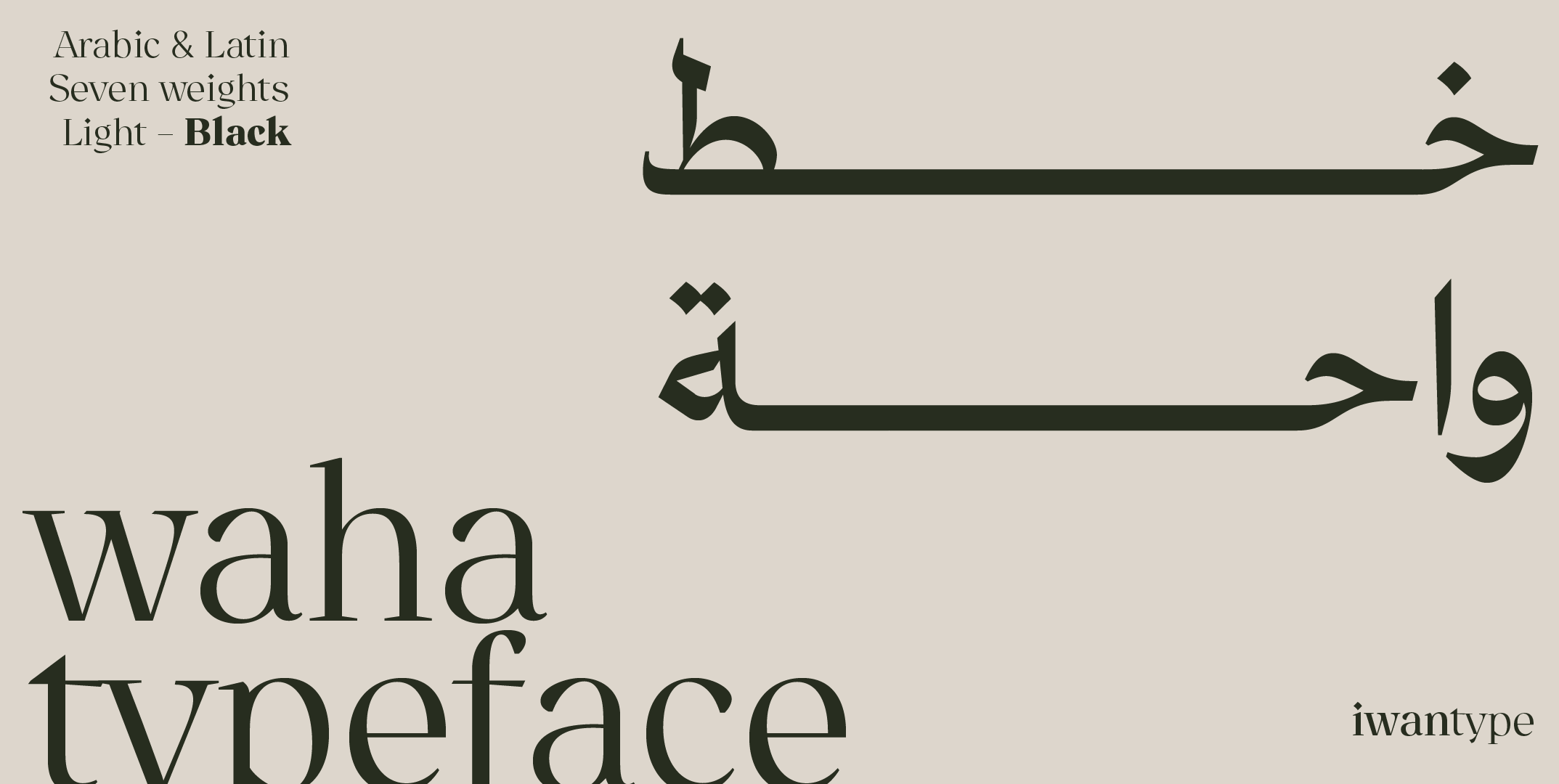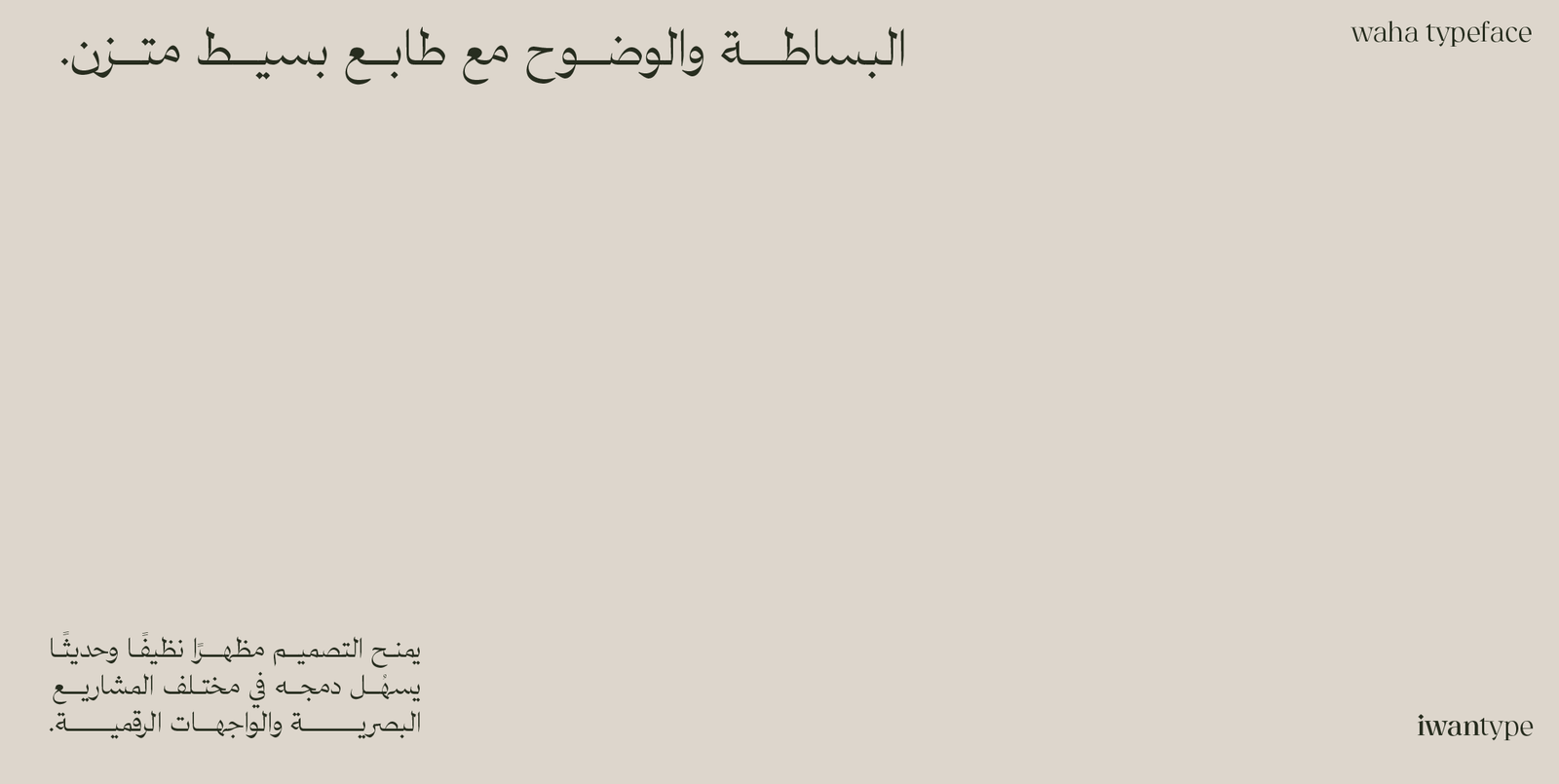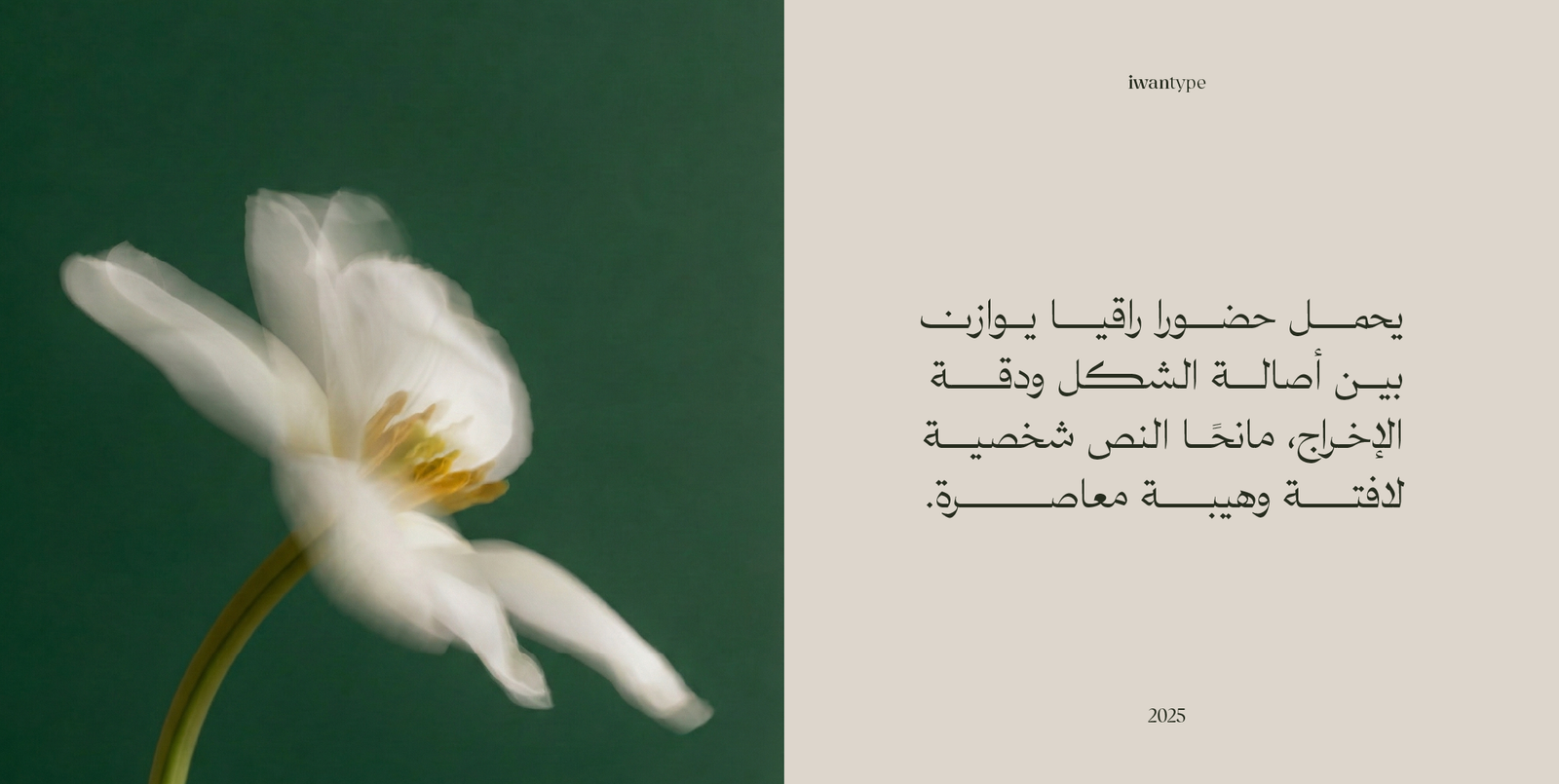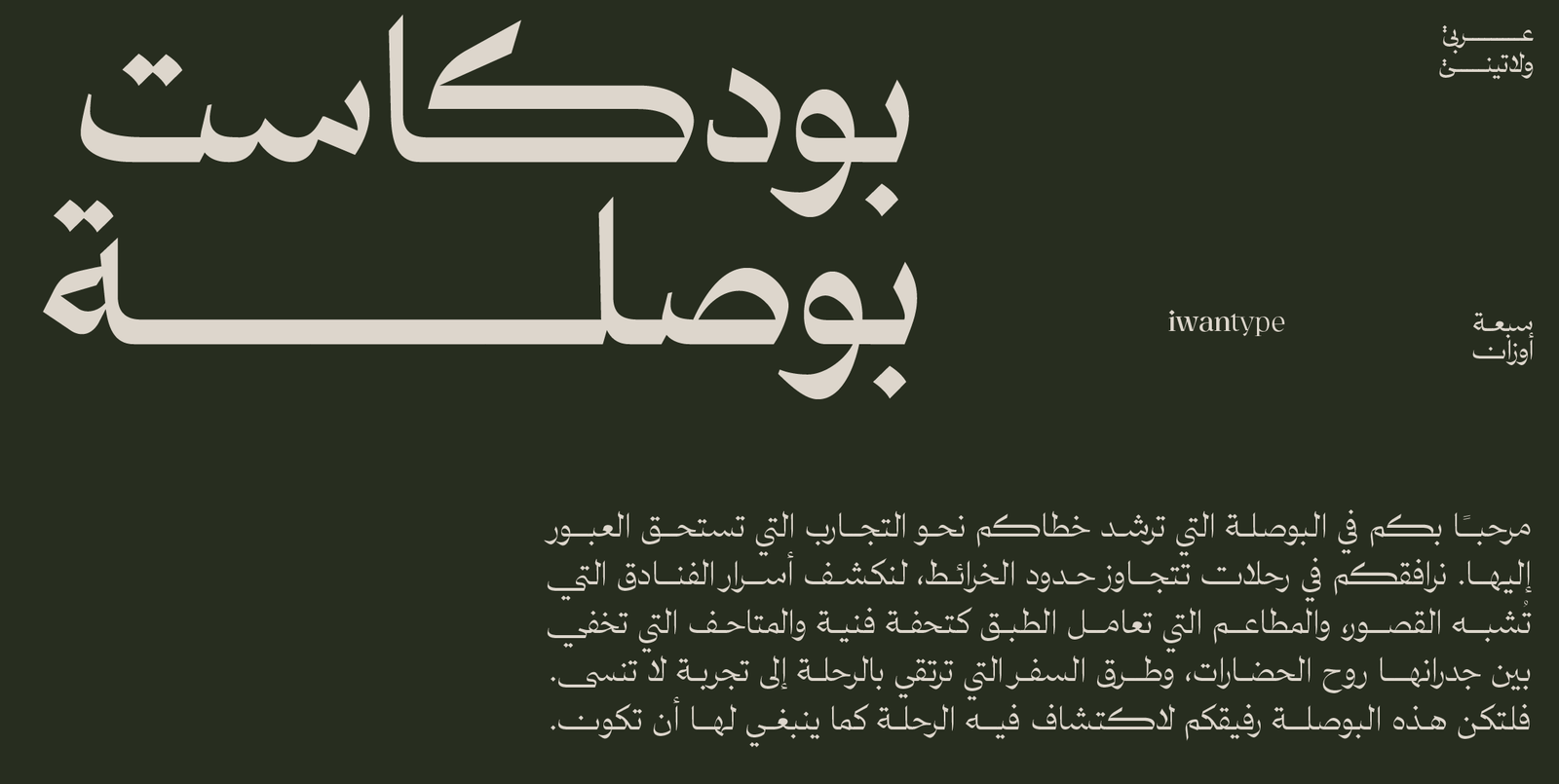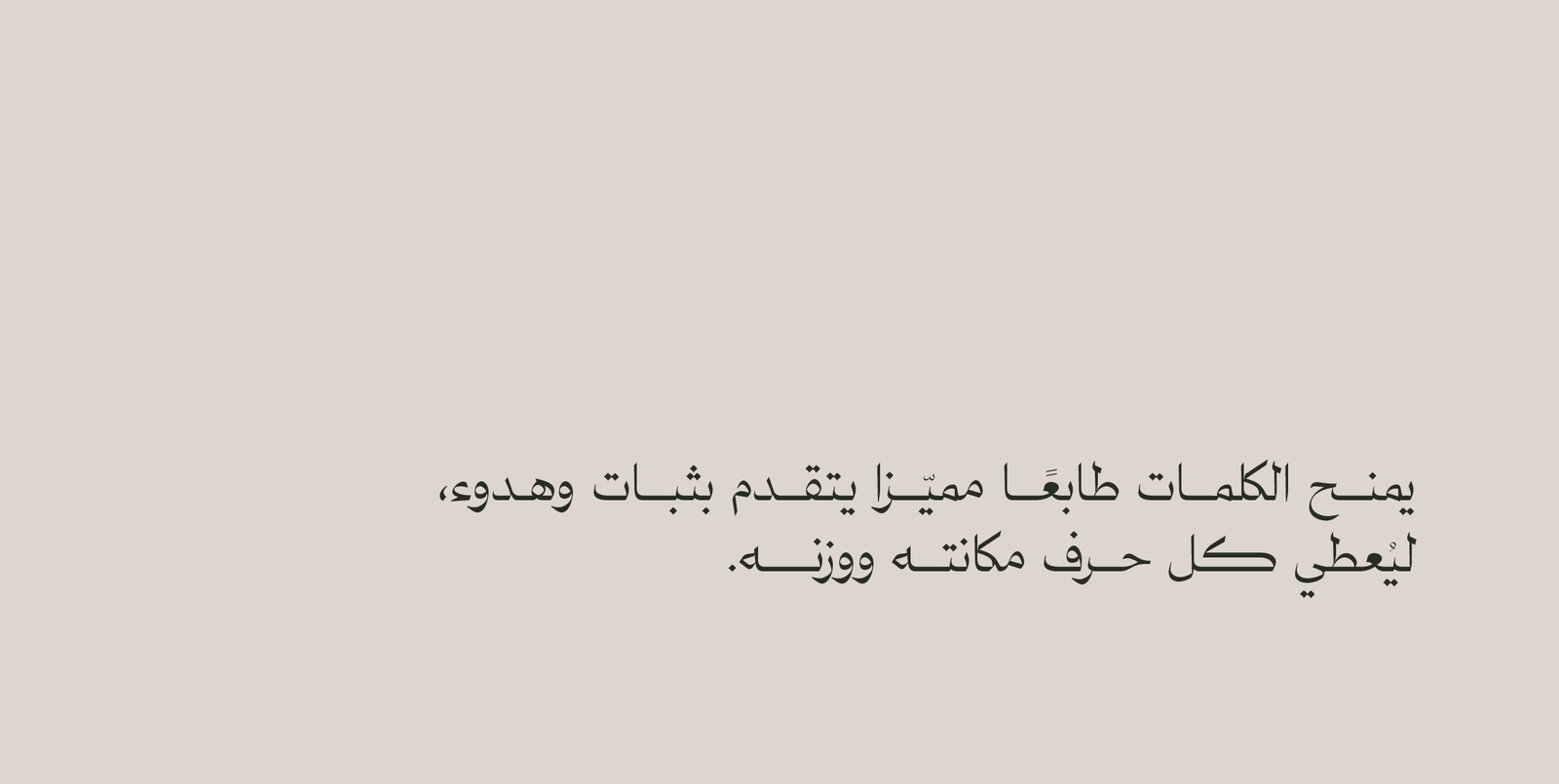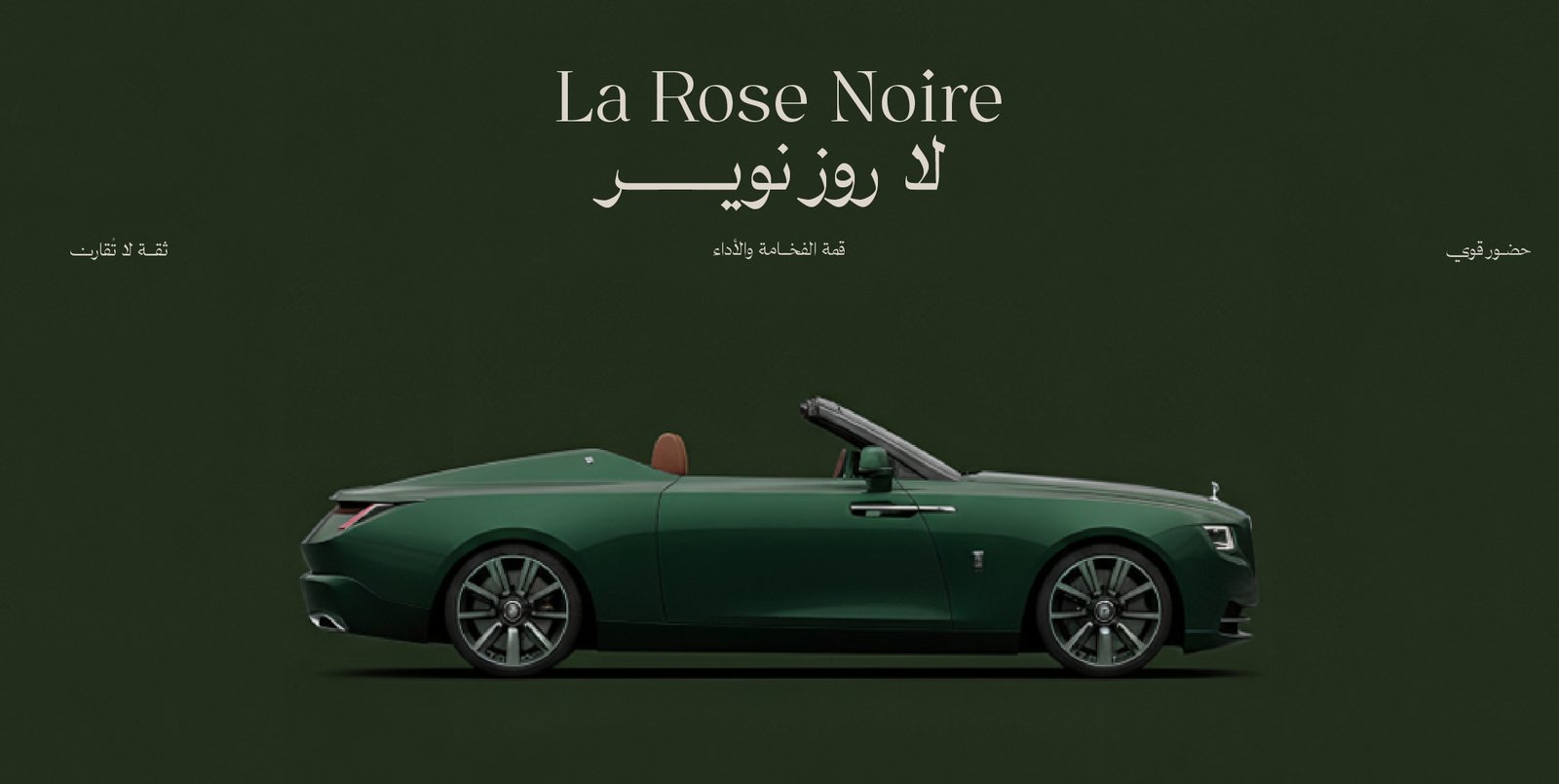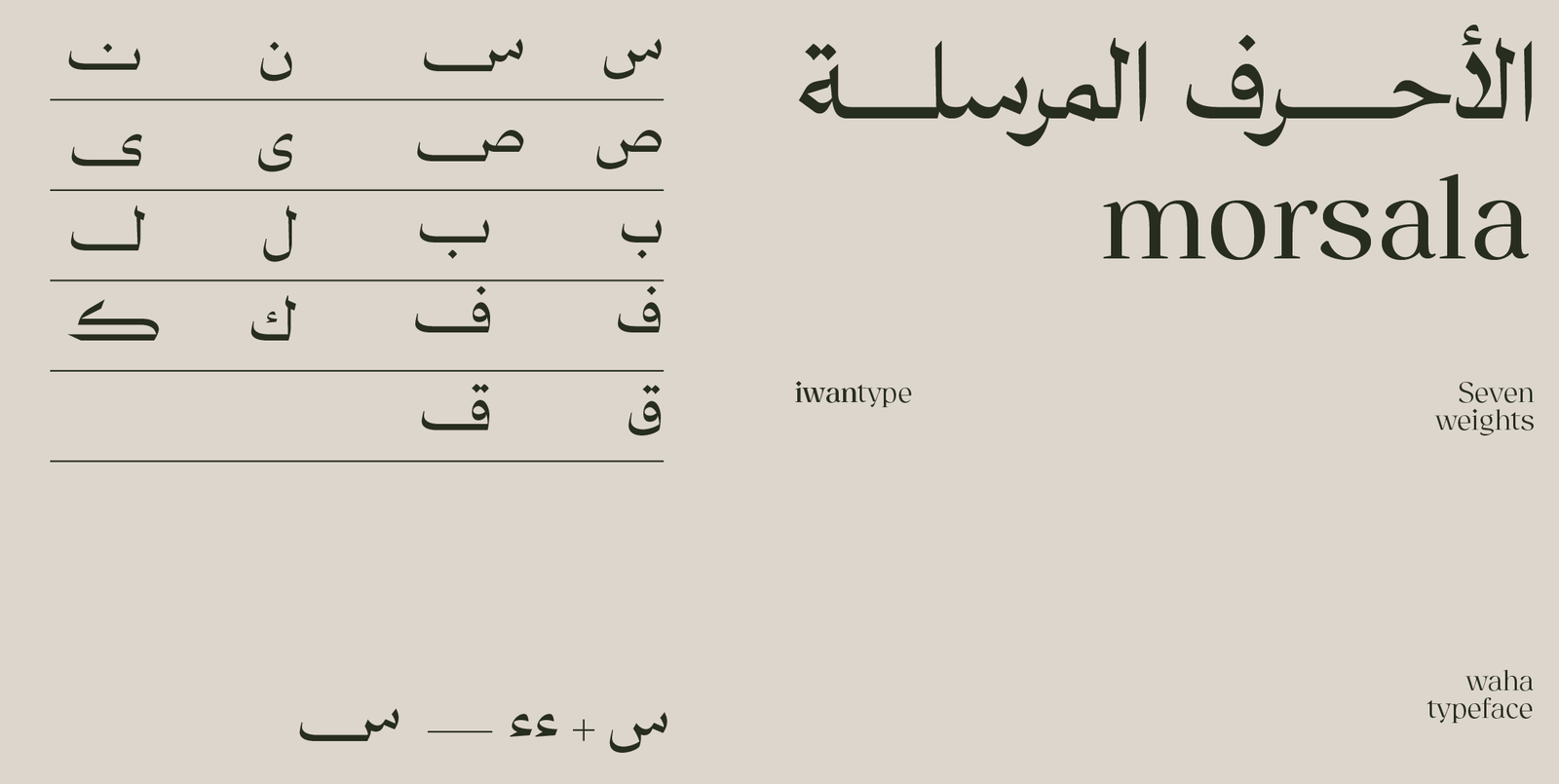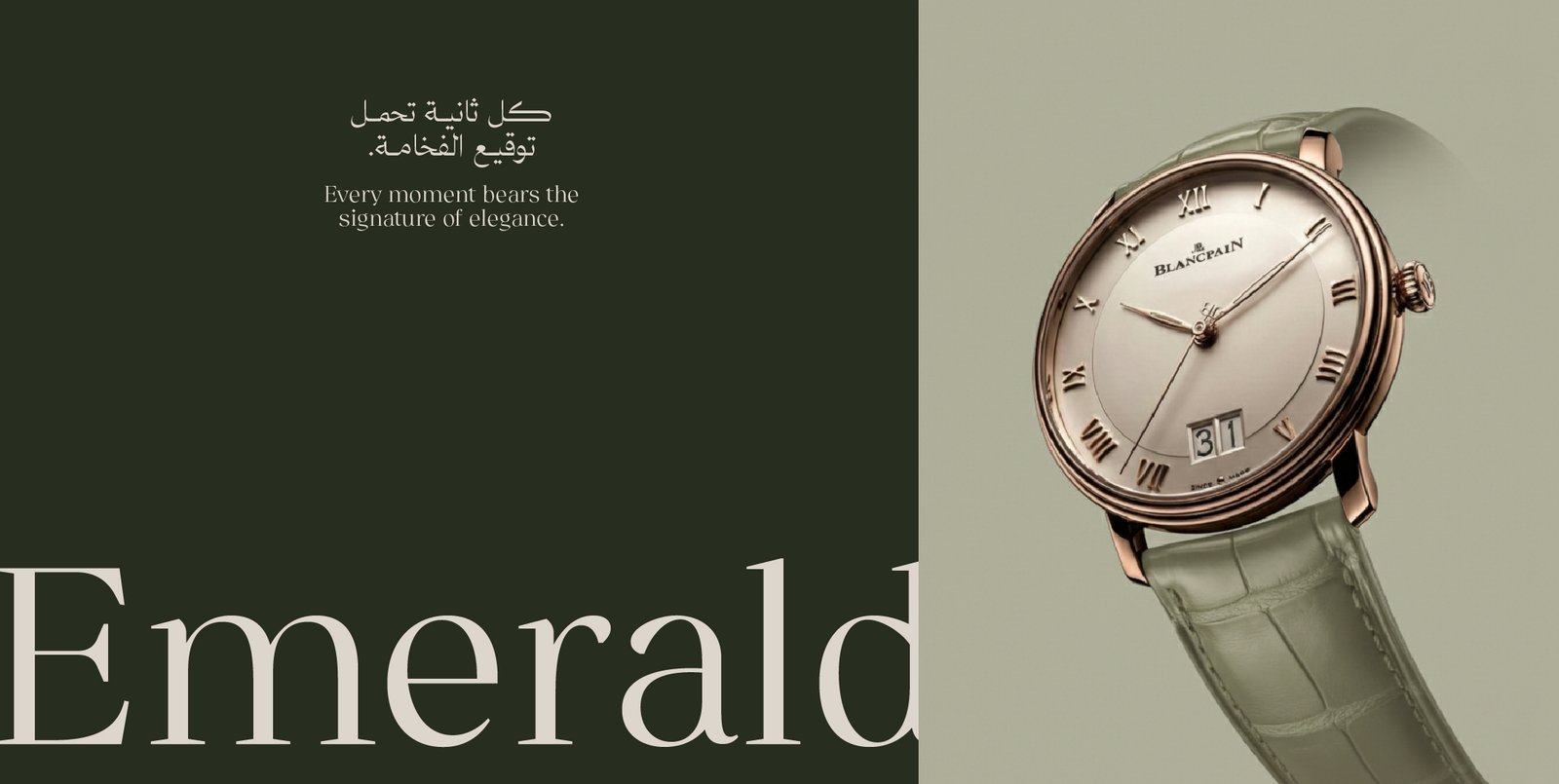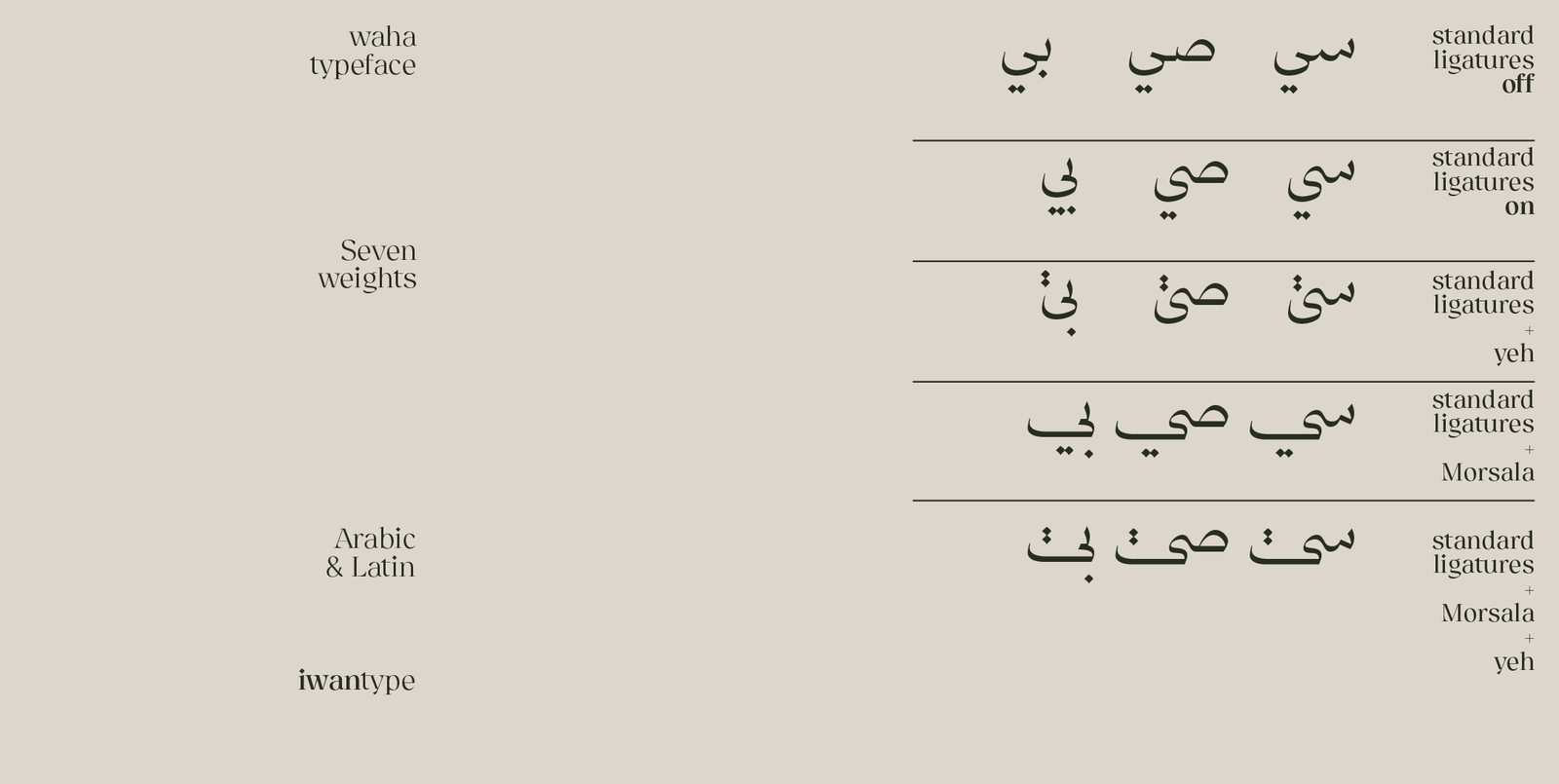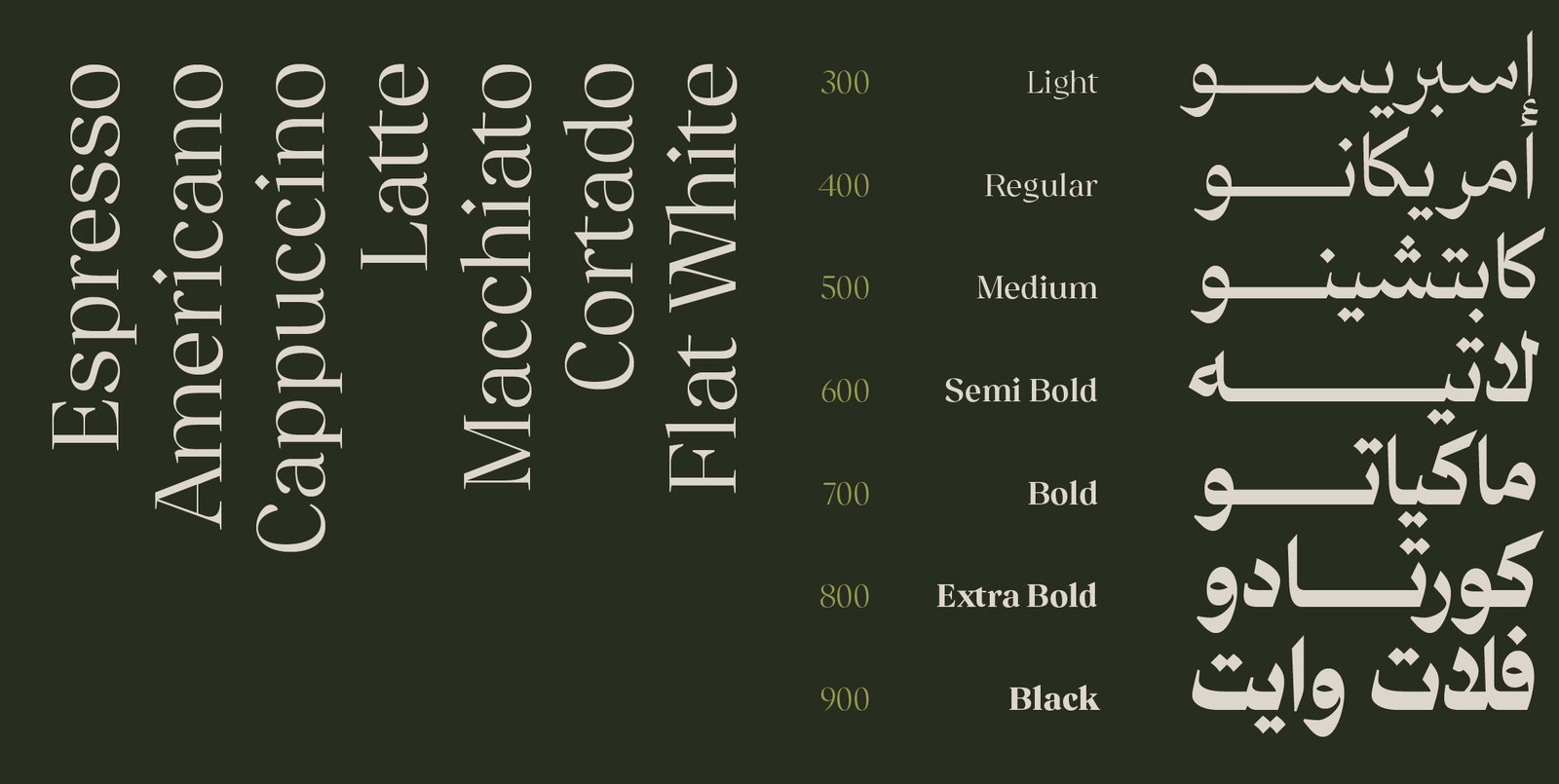
خط واحة الطباعي – waha typeface – خط نسخ
يأتي واحة ليمنح الحرف العربي حضورًا جديدًا مستندًا إلى ذاكرةٍ بصريةٍ عريقة، مستوحاة من أسلوب النسخ الإعلاني في الإعلانات العربية القديمة، تلك التي كانت تزيّن منتجات السبعينات والثمانينات بلمسة فاخرة لا تُنسى.
يقدّم الخط توازنًا بين النقاء الكلاسيكي والفخامة العصرية، بخطوط ممتدة وأناقة متقنة، ليمنح الكلمات طابعًا راقيًا يتناسب مع العلامات التجارية، العناوين التحريرية، وتصميمات المنتجات الفاخرة.
مميزات خط واحة:
يتضمن الخط العديد من مزايا OpenType التي تضفي عليه مرونة وتنوعًا في الاستخدام، مثل:
- نوعان من الأحرف المرسلة: الأول يفعل بإضافة “ءء” بعد الحرف لضمان عمله على Canva والأجهزة المحمولة والتطبيقات التي لا تدعم ميزات OpenType، والثاني من خصائص OpenType (ss05).
- حرف ياء بنزول أقل: يقلل من نزول السطر ويعزّز انتظام النصوص.
- أحرف مركّبة تُحسّن سلاسة التراكيب وتناسق النص.
- سبعة أوزان كاملة تمنح مرونة واسعة في الاستخدام الطباعي.
- نسخة متغيرة (Variable) مع العائلة الكاملة: محور للوزن من Regular إلى Black، ومحور يشغل الأحرف المرسلة.
- يدعم رمز الريال السعودي والريال العُماني ،ويتم تفعيلهما تلقائيًا عند كتابة الاختصارات: ر.س للريال السعودي ر.ع للريال العُماني
اللغات: أكثر من 300 لغة بالحروف العربية واللاتينية
الأوزان: ٧ أوزان + خط متغير